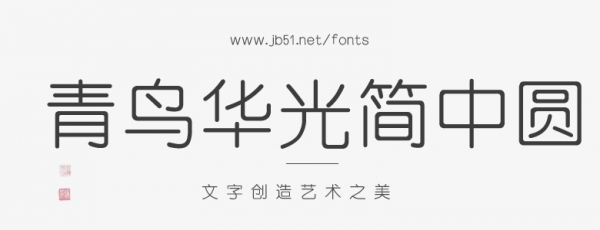
青鳥(niǎo)華光簡(jiǎn)中圓是一種常用的中文字體,其特點(diǎn)是線條流暢、風(fēng)格簡(jiǎn)約大方,非常適合用于文字排版和印刷。該字體采用了清晰簡(jiǎn)潔的字形設(shè)計(jì),配合細(xì)致的筆畫(huà)結(jié)構(gòu),使得每個(gè)字都顯得非常清晰易讀。